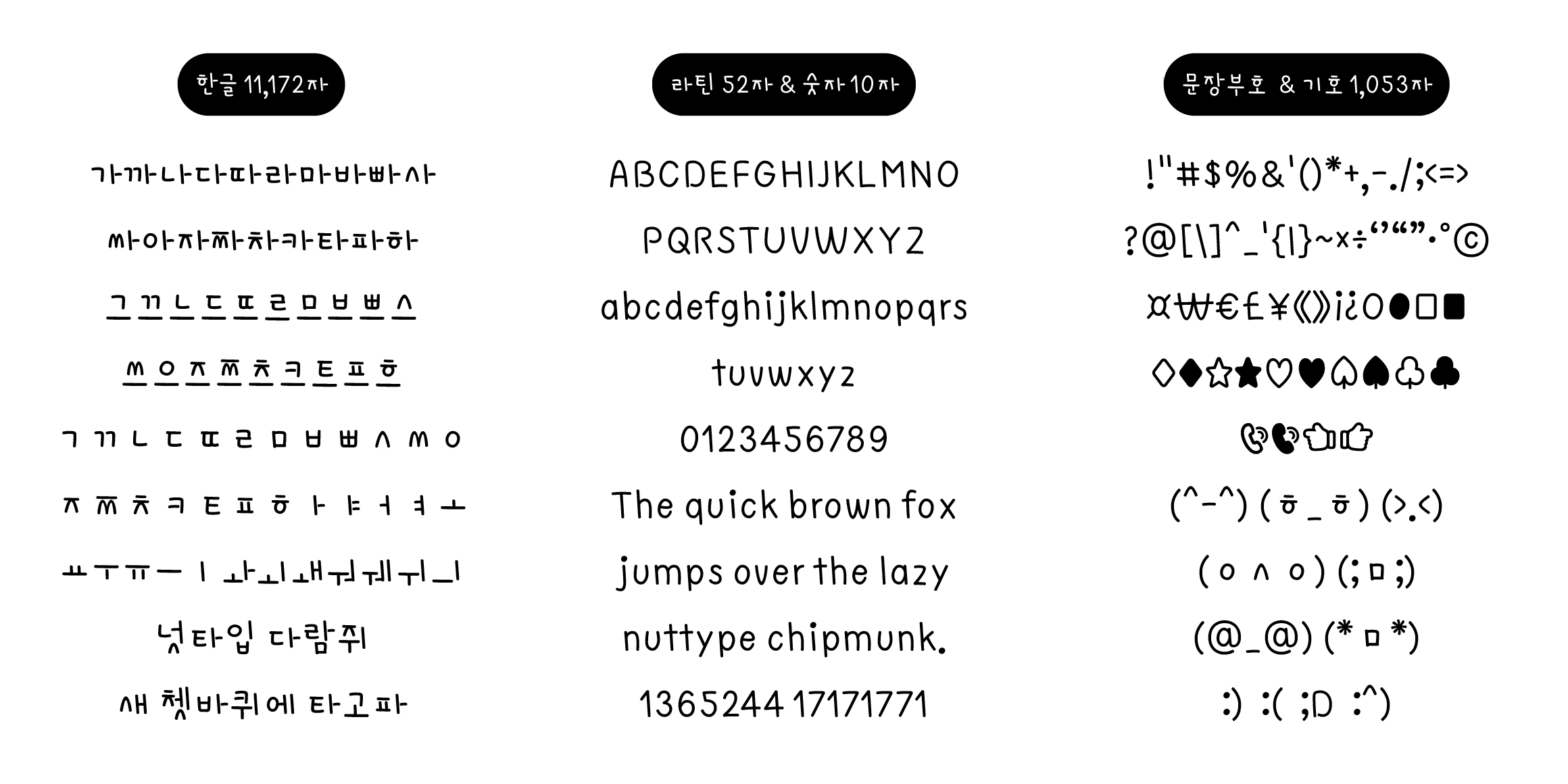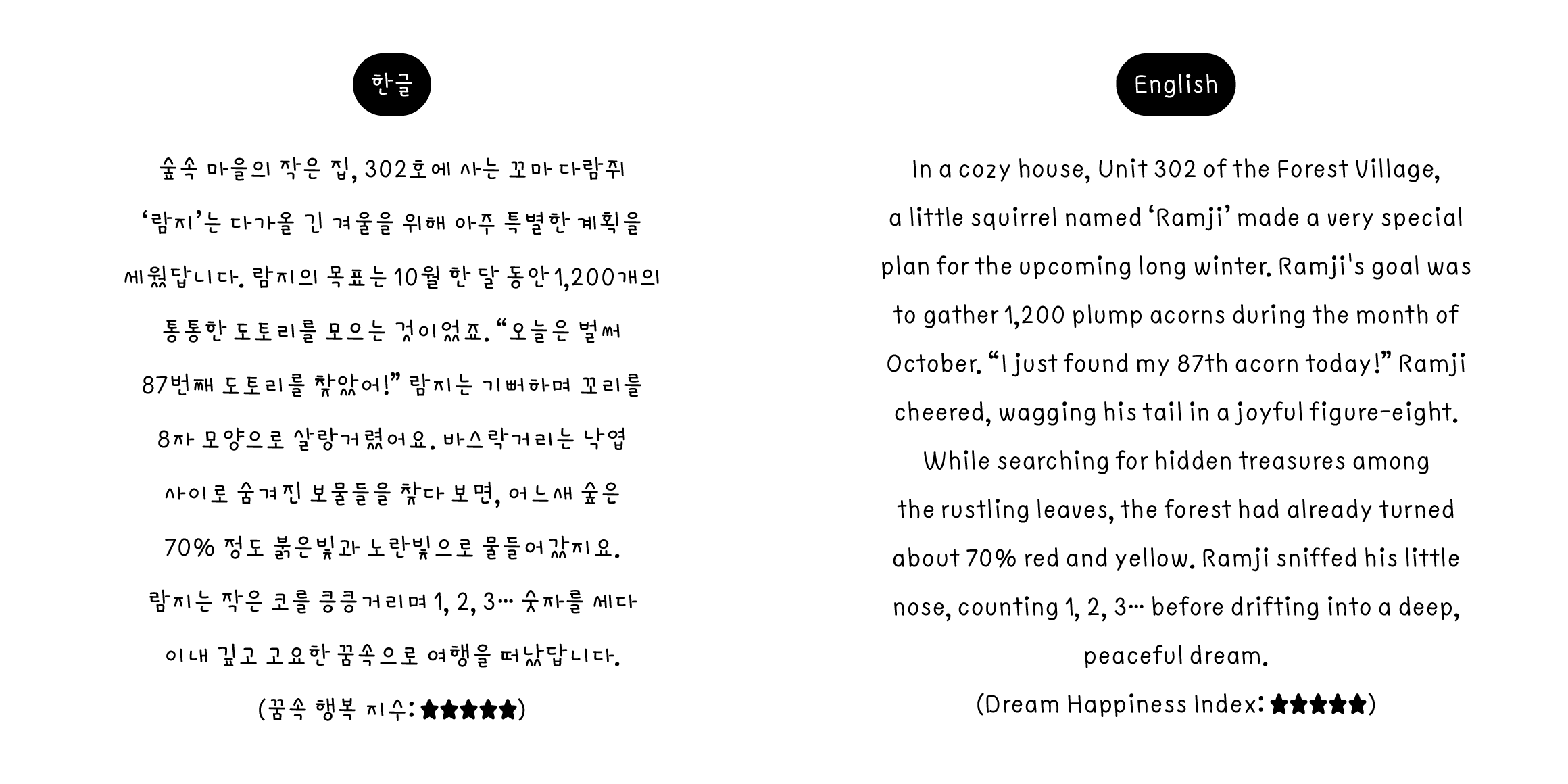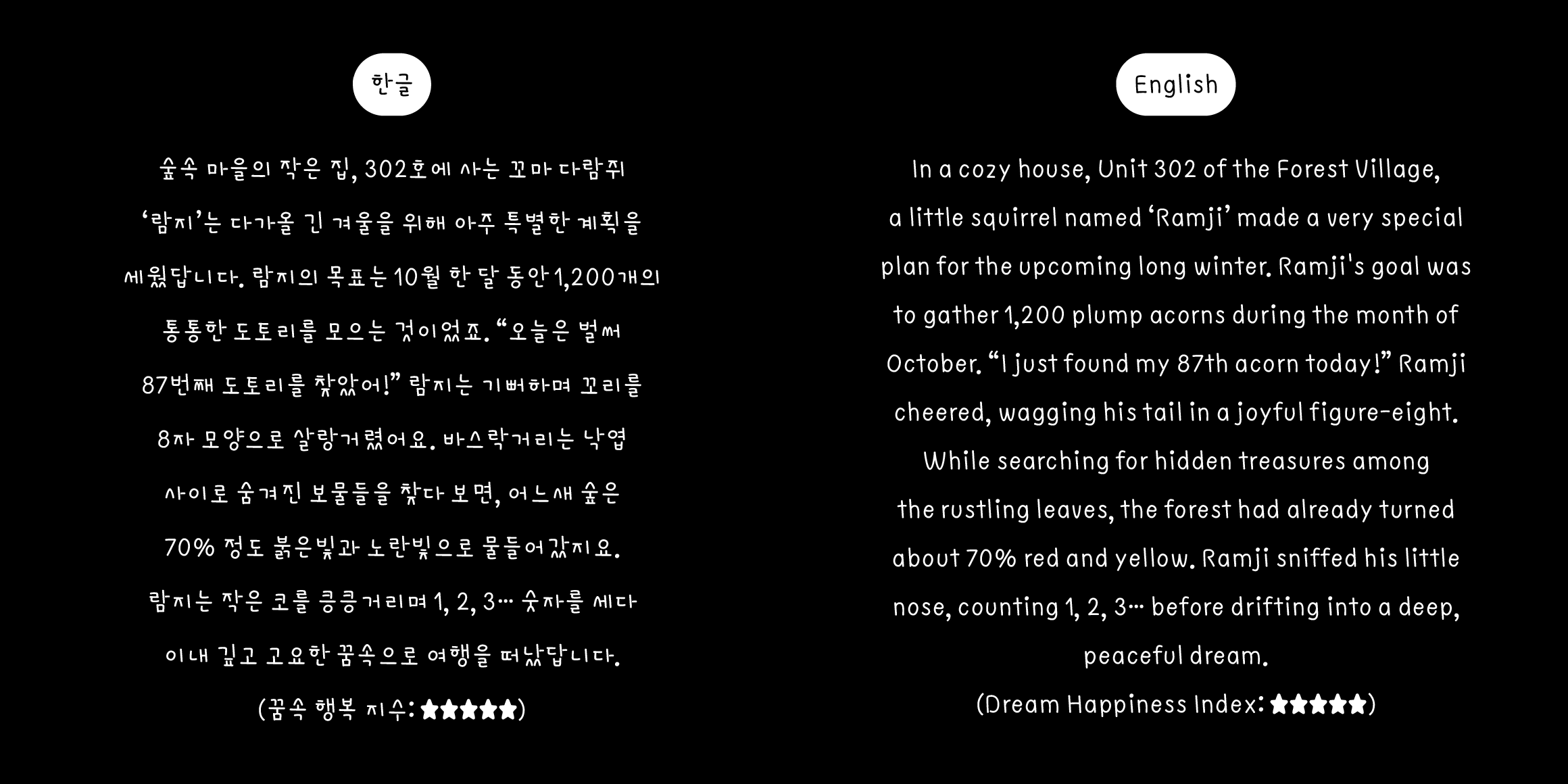
nut 눈사람지
Nuttype
람지는 자기 몸보다 큰 눈덩이를 굴린다. 처음엔 의욕이었다. 두 번째엔 고집이었고, 세 번째쯤부터는 이미 체면 싸움이다. 여기서 멈추면 진다. 눈덩이는 점점 커지고, 람지는 점점 작아진다. 물리 법칙도 눈치 보며 빠져 있다. 이미 주도권이 넘어갔다.
• nut 눈사람지 / nut Snowman Ramji